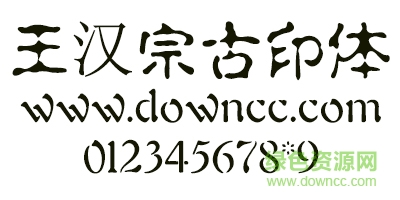
王汉宗古印体
王汉宗古印体字体外形美观,很受网友们的喜爱!这款字体看起来像印刻在上面的一样,字体整体比较舒适。多用来进行设计广告使用!有需要的用户欢迎下载安装。
王汉宗古印体是一款王汉宗类古印字体,字体效果比较正规,印字体给人非常正式的感觉,喜欢行书体字的朋友可以下载使用看看效果如何。
王汉宗古印字体